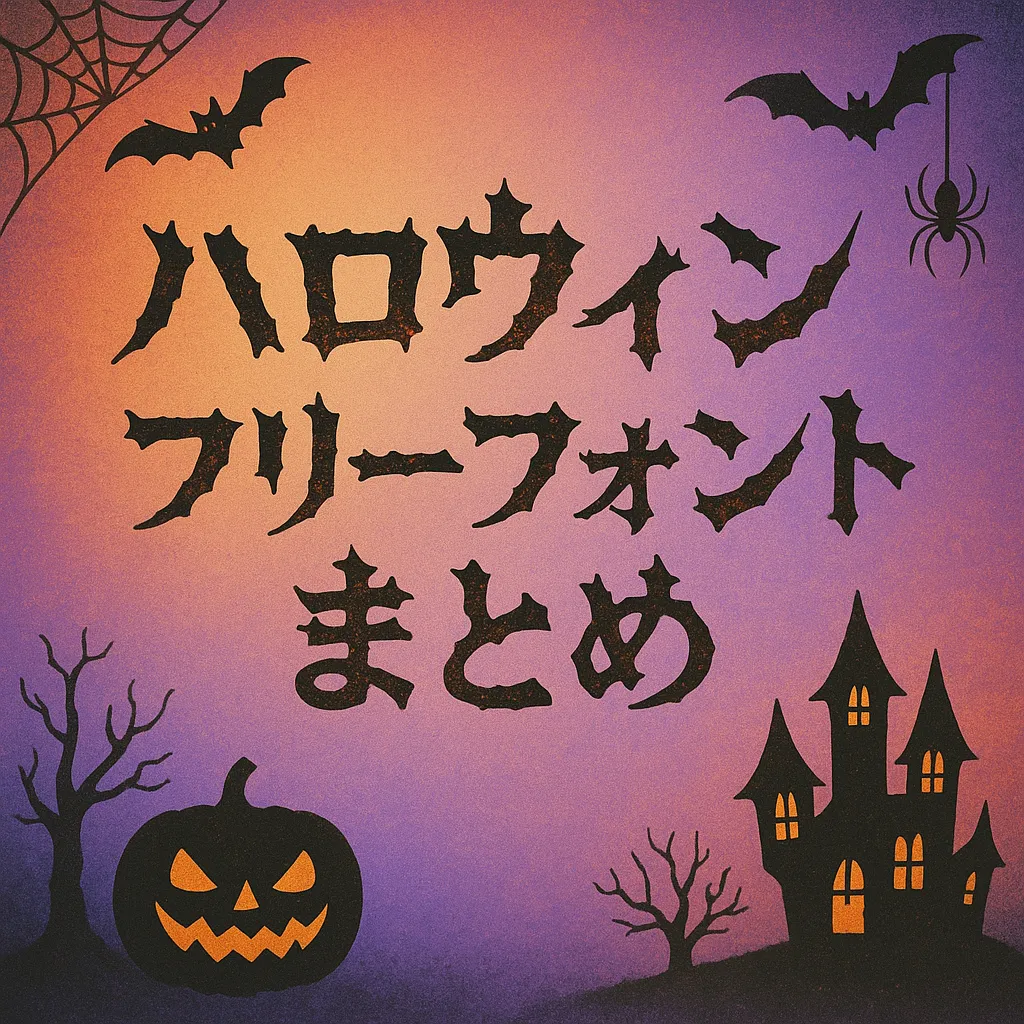
いかほは、丸みを帯びた太めのシルエットが特徴で、親しみやすさと遊び心を演出します。子ども向けイベントのチラシや遊園地のデザインにぴったりです。
玉ねぎ楷書「激」は、筆で力強く書いたような太めの線と墨文字の風合いが特徴です。丸みと角ばりが共存し、柔らかさと力強さが絶妙に混ざっています。和風イベントのチラシや飲食店のメニューにぴったりですよ。
851チカラヅヨクは、筆ペン風の力強い筆致とエッジの効いたデザインが特徴です。スポーツイベントやライブ告知、ストリート系ファッションの見出しに最適です。
怨霊は、トゲのような尖った線構成と手書き風のかすれた質感が特徴です。ホラー系のタイトルや怪談動画のサムネイル、文化祭の演劇ポスターにもぴったりです。
殴り書きクレヨンは、クレヨンで書いたようなザラついた線とゆるいバランスが特徴で、手描き感があたたかさを演出します。子ども向け教材やアート系フライヤー、カフェの手書き風ポップにぴったりです。
やなぎ体は、しなやかな縦の流れと鋭い筆先が特徴で、幻想的な雰囲気を演出します。和風ファンタジーや舞台公演のタイトル、個性的なロゴデザインにもぴったりです。
やきとりは、筆で書いたような力強い太字が特徴で、居酒屋の看板やメニューにぴったりです。手書きの温かみがあり、ポスターやチラシの見出しにも勢いを与えます。
ピグモ01は、図形的でユニークなデザインが特徴のフォントです。視覚的インパクトがあり、ポスターやイベント告知、サブカル系のロゴ、デザイン重視のパッケージなどに最適です。
白舟髭隷は、力強い筆致と勢いのある線構成が特徴で、リアルなかすれとにじみが魅力です。時代劇や歴史系コンテンツのタイトル、和風の店舗ロゴ、祭りのビジュアルにぴったりです。
チェリーチェリーは、直線のみで構成された大胆なデザインが特徴のフォントです。音楽イベントやアートブックのタイトルに最適で、視覚的にスタイリッシュな印象を与えます。
コトダマは、精霊のような有機的シルエットが特徴のフォントです。視認性よりも造形美を重視し、タイトルやロゴ、ホラーやファンタジー作品のビジュアル演出にぴったりです。
オバケは、ギザギザと尖った装飾が特徴のこのフォントで、ホラーや怪談の雰囲気を演出します。細身でシャープなラインが冷たさを強調し、イベントやハロウィンの装飾にもぴったりです。
じんふぁんしーぴの-Rかなは、木目調のユニークな質感と手書き風デザインが特徴です。ポップで親しみやすいフォルムが、クラフト系雑誌や子ども向けイベントのチラシにぴったりです。
g_コミックホラー恐怖(R)-教漢版は、鋭角的で不安定なデザインが特徴のフォントです。ホラー漫画のタイトルやお化け屋敷のビジュアルにぴったりで、怪奇系の演出に最適です。
らくまにらくがきフォントは、手描き感あふれるラフな筆跡と丸みを帯びた柔らかな字形が特徴です。手紙やメッセージカード、カフェのメニューなどにぴったりで、親しみやすい印象を与えます。
過充電FONTくれよんは、クレヨンで描いたようなざらつき感とふんわり丸みを帯びたデザインが特徴です。手書きの温かさがあり、子ども向けの絵本やナチュラル系雑貨のPOPにぴったりです。
しろくまフォントは、筆書き風のラフなラインと温かみのある形が特徴で、モダンと伝統が融合したデザインです。和風テイストのタイトルや飲食店のメニューにぴったりですよ。
源界明朝は、かすれ加工が施された明朝体で、鋭角的なセリフと縦長の骨格が特徴です。ホラーやミステリーのタイトル、アナログ感を出したい紙雑貨にぴったりです。
効果音フォントは、マンガの擬音風演出が特徴で、文字に斜線が入り動きを表現します。大胆なシルエットと視覚的なインパクトがあり、マンガやアニメのロゴ、特撮タイトル、イベントポスターに最適です。
バンバンは、角ばってシャープなデザインが特徴で、近未来感を演出します。均等な文字幅と大胆な線が視認性を高め、ゲームやアニメのタイトルロゴ、ポスター、商品パッケージに最適です。